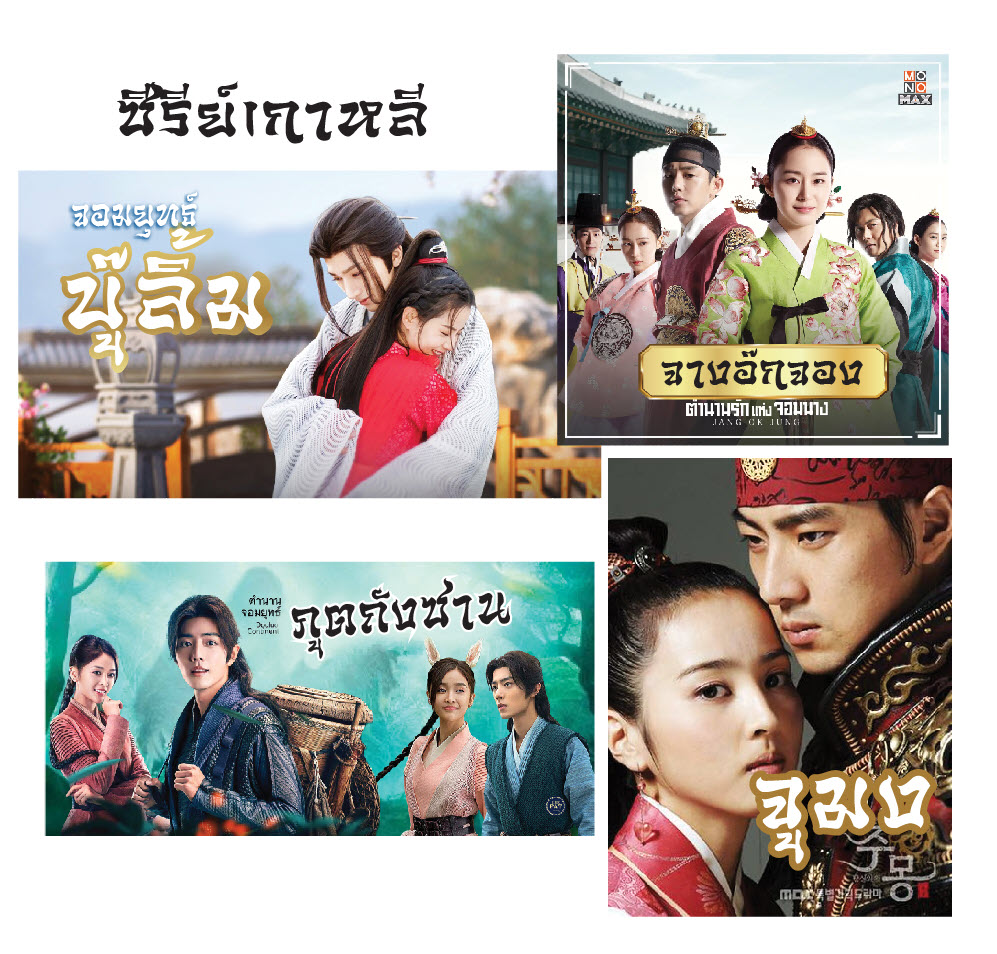
แรกเรื่มเดิมทีกะจะเขียนฟอนต์อารมณ์ซุนหงอคงวานรเทพไร้พ่าย เขียนไปเขียนมาจบที่สามก๊กเฉยเลย55         ไม่ไปต่อแระจะไหลไปงานซีรีย์เกาหลีแระ  งานจะเป็นงานหางสะบัดอารมณ์ ไซอิ๋วแต่งชุดรบพร้อมปะทะพริ้วไหวแจกฟรี! สำหรับใช้ส่วนตัวครับ ต้องการใช้งานเชิงพาณิชย์ สนับสนุนได้ 300บาท มีไทย-อังกฤษ เลขไทย-อังกฤษครับเขียนไว้สำหรับงานป้ายไวนิลรอบที่ใช้จริงตอนแรกๆก็เทศกาลถือศิลกินเจครับสนับสนุนความตั้งใจของเราผ่านทาง